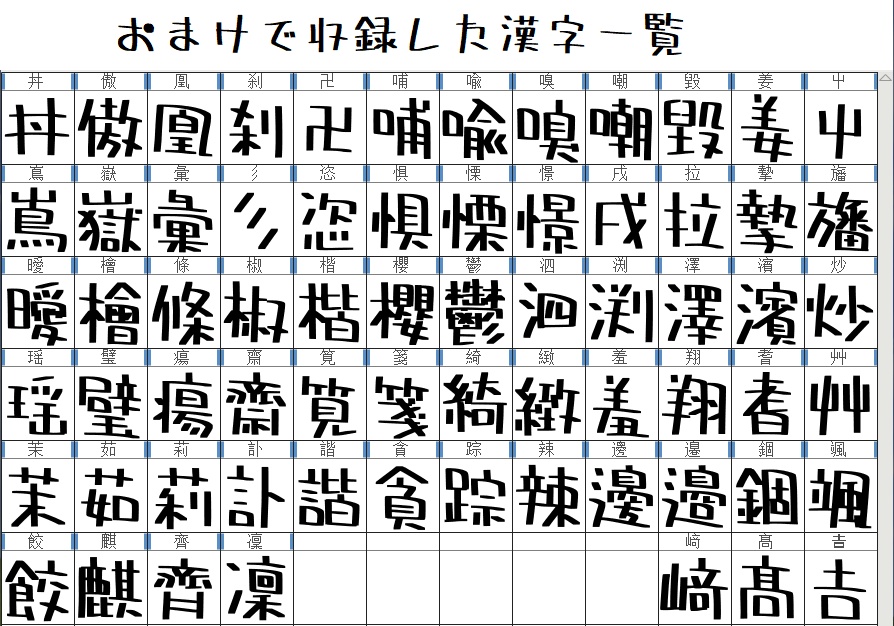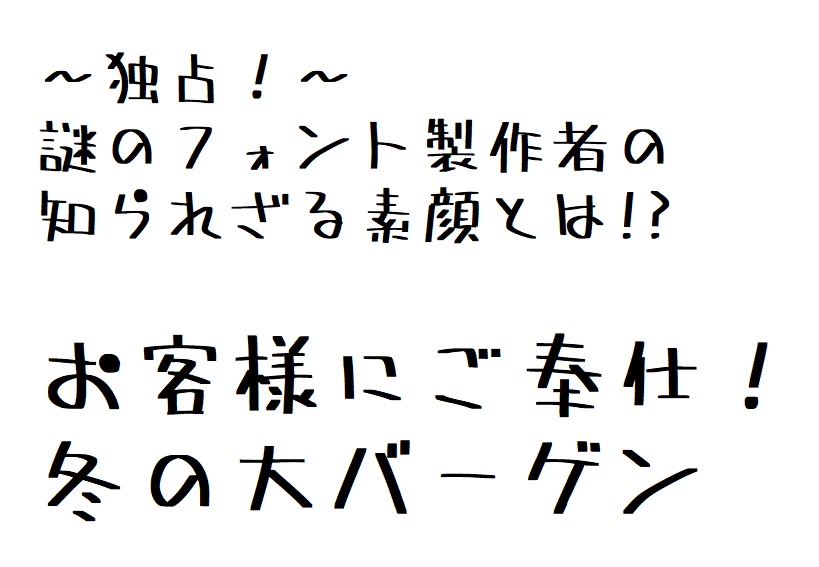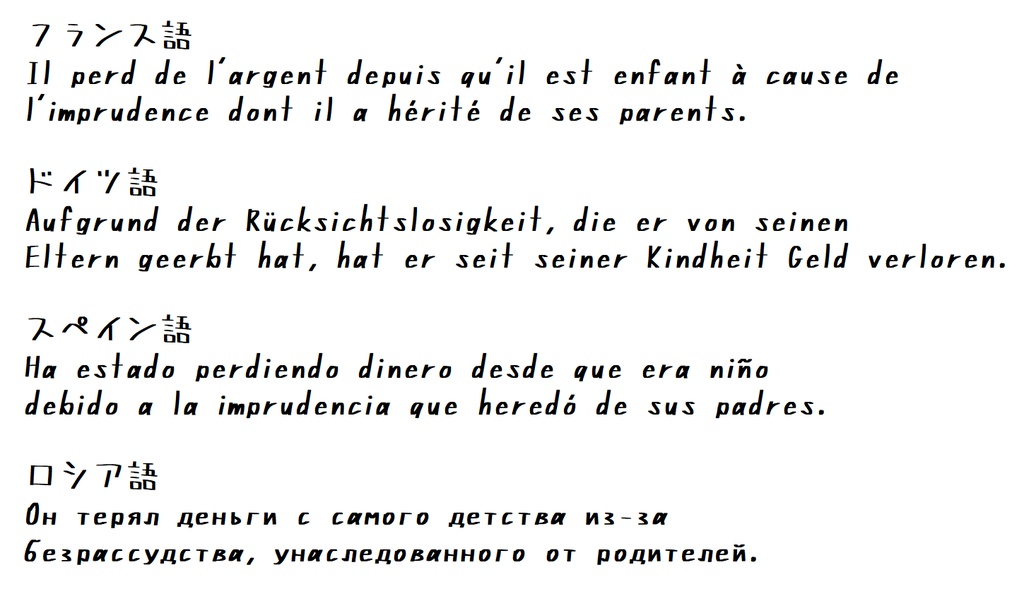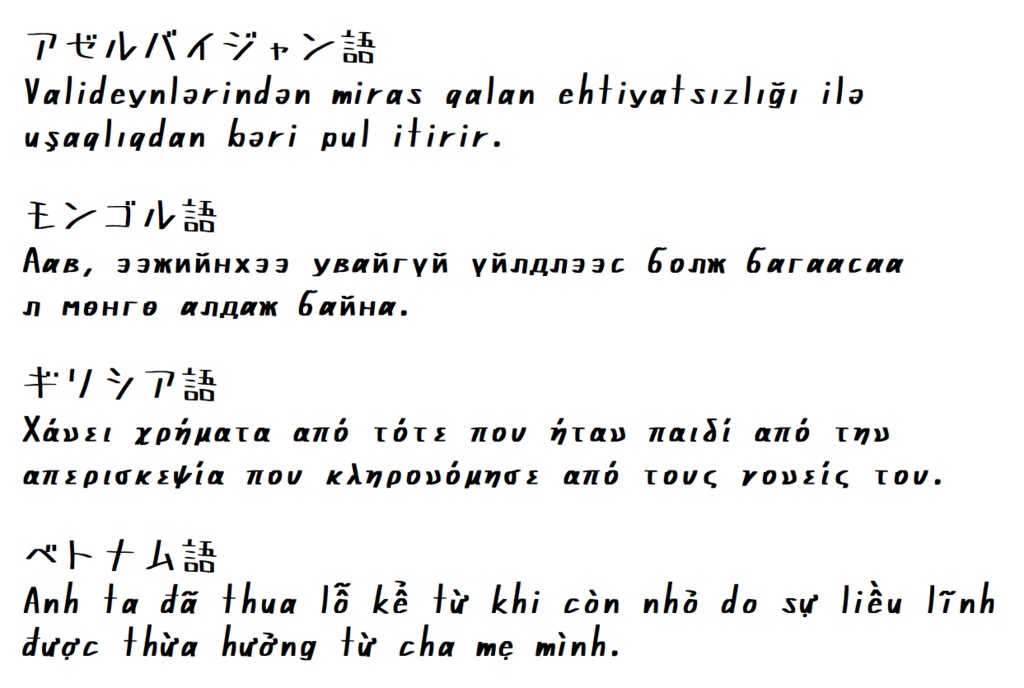
全員集合!ポップ体(JIS第1水準漢字対応版)※2024/11/23訂正と更新あり
「全員集合!ポップ体」を無料公開します。 80年代のテレビ番組で使用されたような手書き文字をイメージして 製作した手書き文字フォントです。 商用利用可能(自己責任)、反社会的利用は禁止でお願いします。 ※2023/10/29更新:主要なヨーロッパの言語と モンゴル語、ベトナム語を書くためのアルファベットを追加しました。 ※2023/11/06訂正と更新:「脇」の字を修正しました。 ※2023/11/29更新:JIS第1水準漢字全部と「泗」「旛」「耆」を追加。 ※2024/11/23訂正と更新:「懐」の字を修正しました。
「全員集合!ポップ体」を無料公開します。
80年代のテレビ番組で使用されたような手書き文字をイメージして
製作した手書き文字フォントです。
※2023/10/29更新:主要なヨーロッパの言語と
モンゴル語、ベトナム語を書くためのアルファベットを追加しました。
※2023/11/06訂正と更新:「脇」の字を修正しました。
※2023/11/29更新:JIS第1水準漢字全部と「泗」「旛」「耆」を追加。
※2024/11/23訂正と更新:「懐」の字を修正しました。